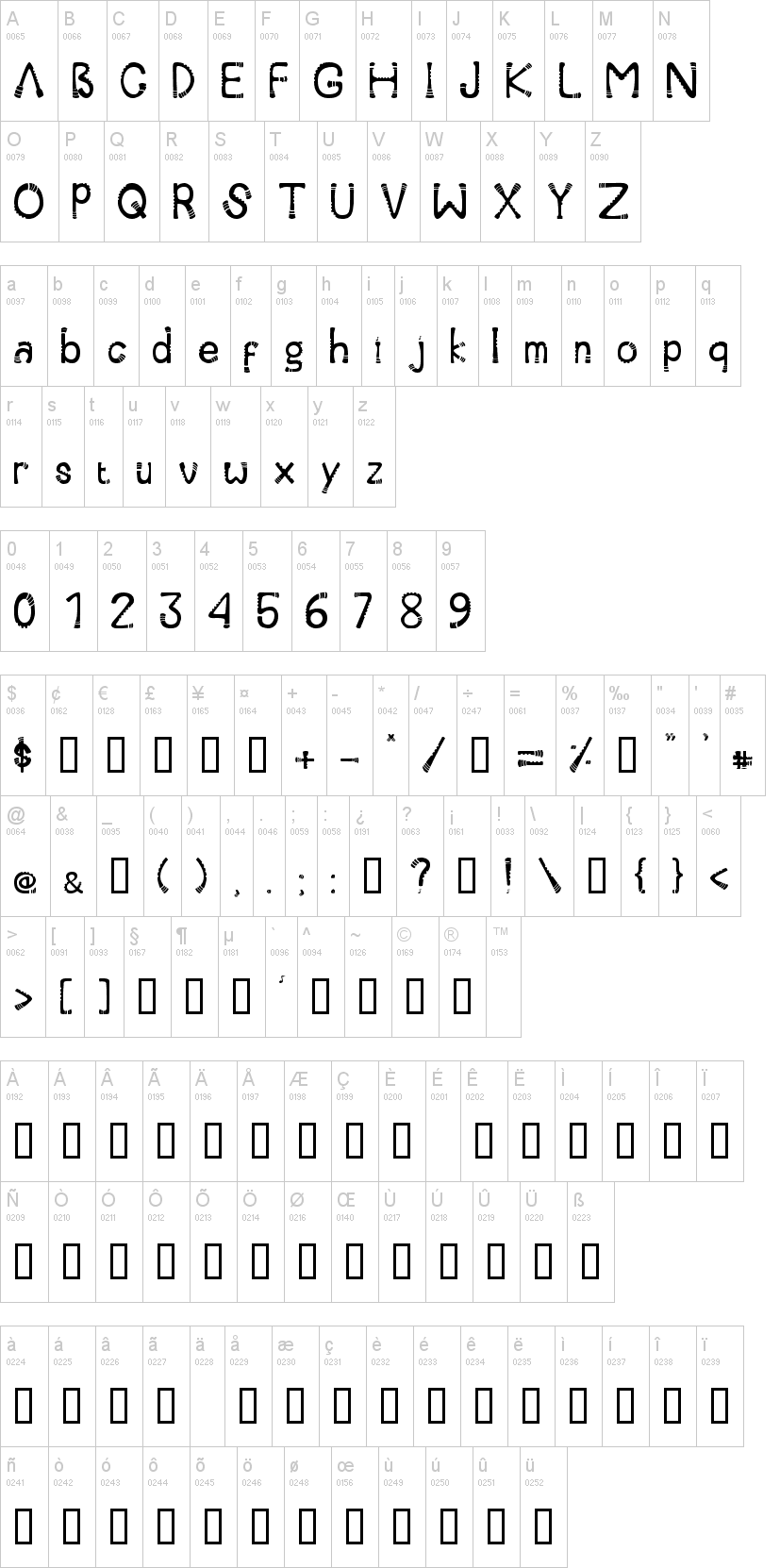
Serunaitype 字体是一种日本的抽象类型字体,由日本设计师Serunai设计。它的特点是抽象的外观和极简的风格,具有极强的可读性和可辨识度。Serunaitype 字体有多种版本,每个版本都有自己独特的设计特征,如极简、动态、现代、简洁等。它可以用于各种不同的应用,如平面设计、网页设计、标志设计、打印设计等。内容介绍
Serunaitype是一款非常不错的手写艺术字体,具有很好的视觉感,适合于文化类的宣传设计、商业类品牌的广告和产品包装设计以及个性化文字排版等较多场景。